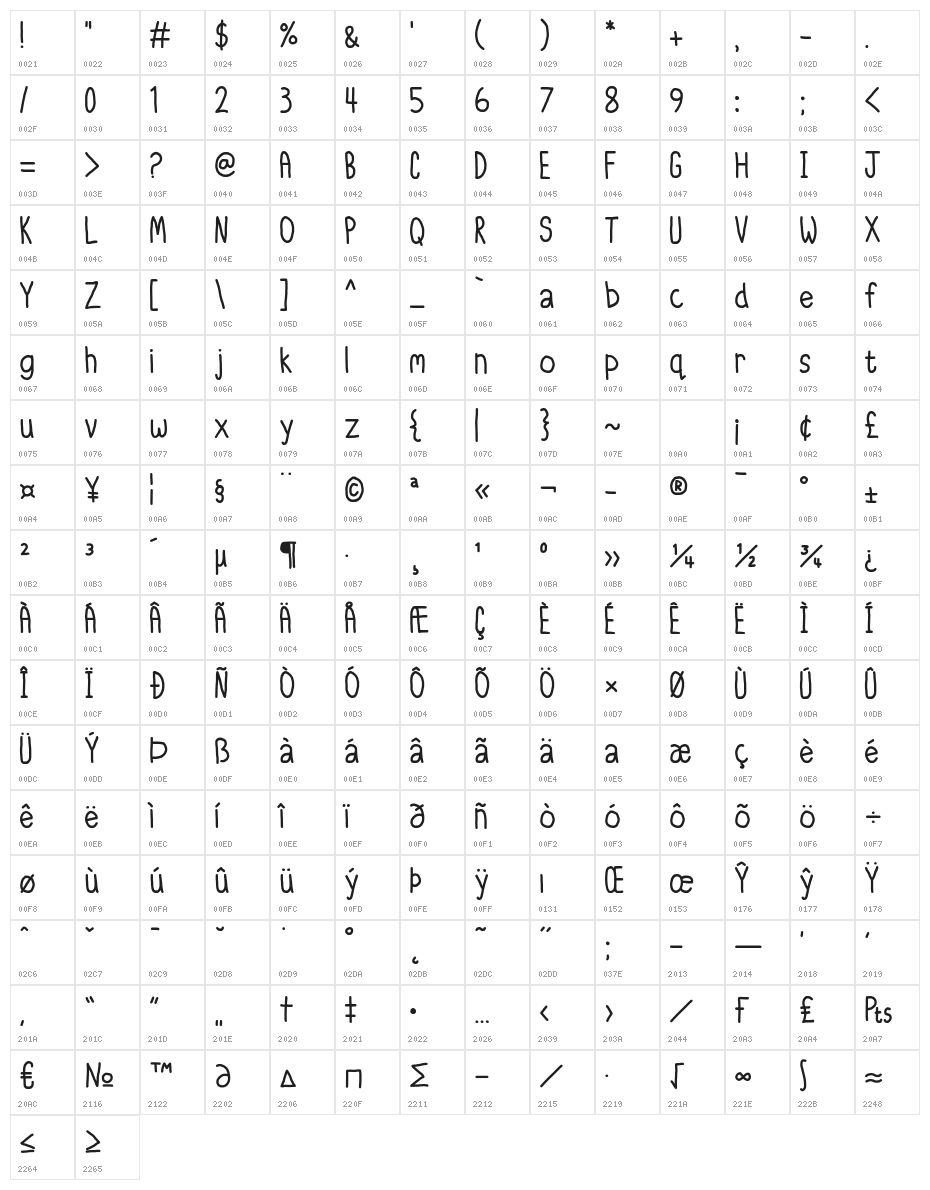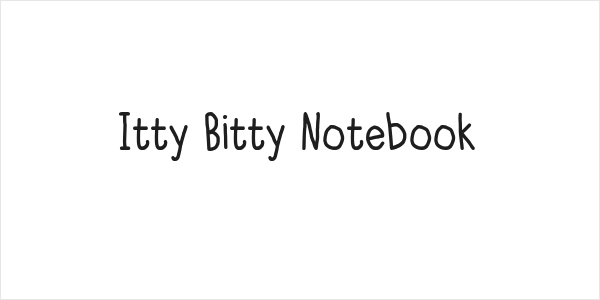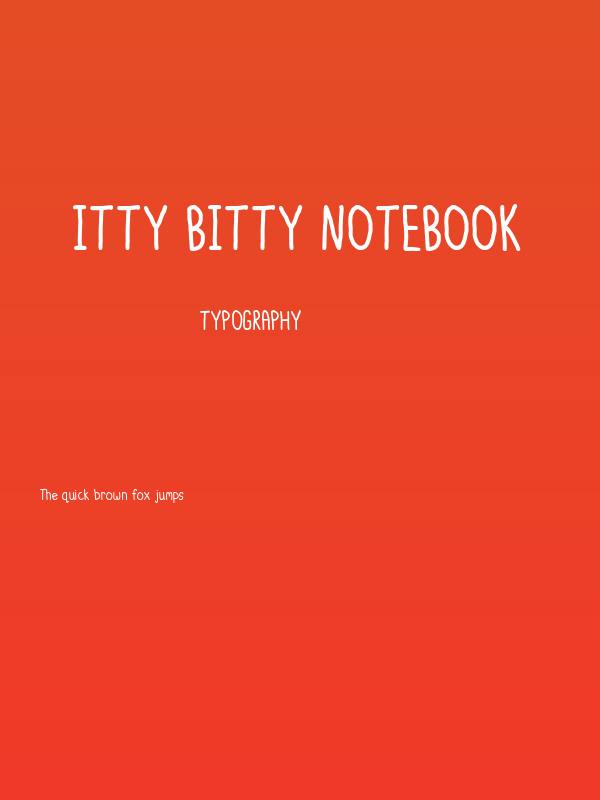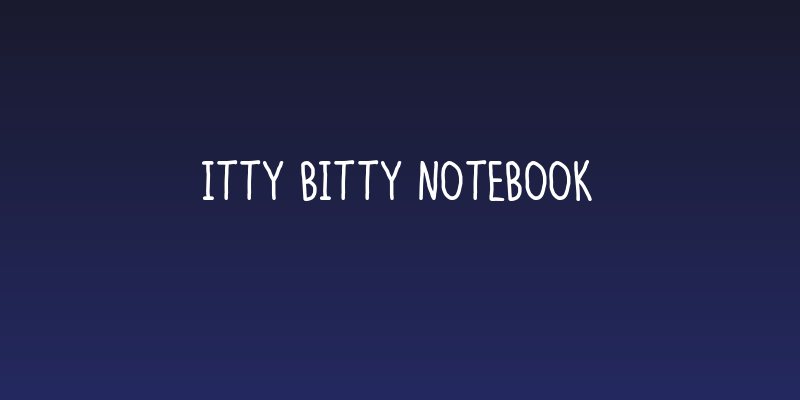
Itty Bitty Notebook Font
| Gesamtstil | Casual |
| Anwendungsfall | Headlines, Informal text, Personal projects |
| Vorgeschlagene Projekte | Ideal for children's books, greeting cards, personal blogs, and informal branding. |